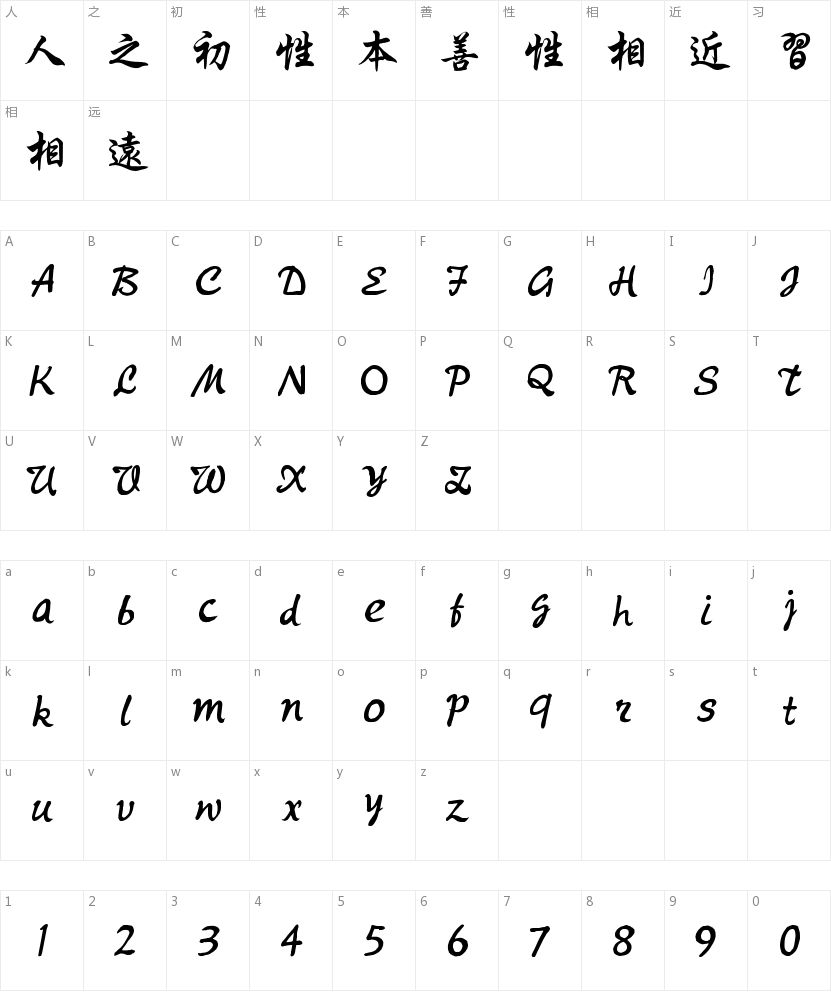
腾祥伯当行楷繁是一款比较流行的汉字字体,由腾祥伯当行字体工作室设计,属于行楷类字体。腾祥伯当行楷繁字体的特点是字形优美,笔画清晰,笔划自然,笔画粗细均衡,字体结构精细,字形稳定,符合汉字书写规范。由于字形精致,符合汉字书写规范,腾祥伯当行楷繁字体在汉字书写中得到了广泛的应用,尤其是在书法、篆刻、绘画、广告、印刷等领域。文件名:TengXiangBoDangXingKaiFan-1.ttf
腾祥伯当行楷繁是一款非常不错的手写艺术字体,具有很好的视觉感,适合于文化类的宣传设计、商业类品牌的广告和产品包装设计以及个性化文字排版等较多场景。